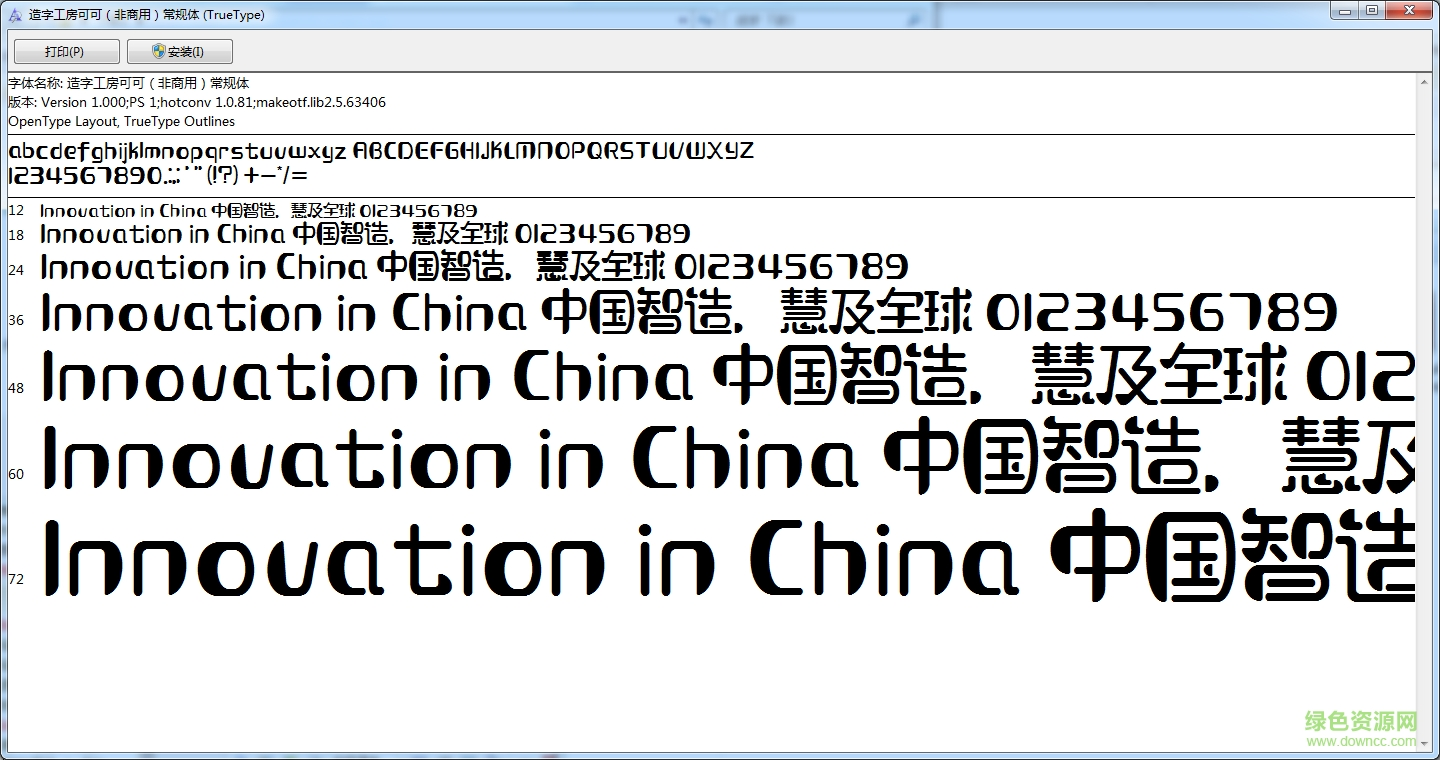
mfkeke是什么字體?mfkekenonconmercial regular字體又叫造字工房可可常規(guī)體,該字體方圓結(jié)合得當(dāng),筆畫粗細(xì)變化自然,趣味盎然,靈動(dòng)可愛,用在海報(bào)或平面上效果非常棒!
1.設(shè)計(jì)師在此款字體筆畫上做了大膽的嘗試創(chuàng)新;
2.點(diǎn)線面的穿插、像一首有節(jié)奏的樂章、起承轉(zhuǎn)合恰到好處,活潑而飽滿;
3.筆畫渾圓淳和、內(nèi)蓄勁力,在保持整體風(fēng)格中大膽變幻、勢(shì)合形離;
4.部分筆畫的斷開更加凸顯字體的風(fēng)格特點(diǎn);
5.此款字體適用于主副標(biāo)題及個(gè)性品牌的設(shè)計(jì)中!